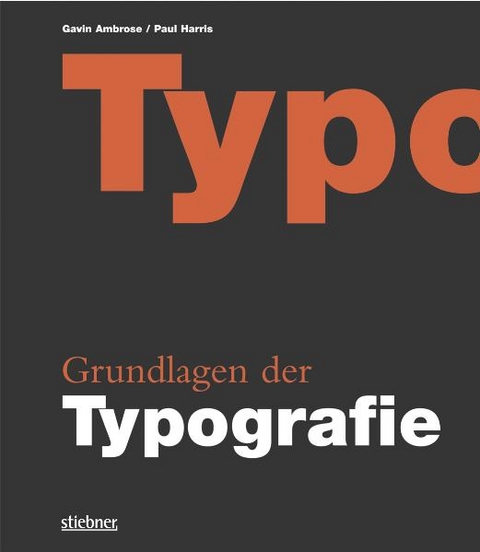
Grundlagen der Typografie
'Gute Typographie ist so, wie ein guter Diener gewesen sein mag: da und doch nicht bemerkbar; unauffällig, aber eine Voraussetzung des Wohlbefindens …', so formulierte es einmal Jan Tschichold. Um dieses hohe Ziel in der Gestaltung mit Schrift zu erreichen, ist typografisches Basiswissen allerdings unabdingbar. Die Grundlagen der Typografie faßte Gavin Ambrose daher in einem praxisnahen und gestrafften Band zusammen, der anhand vieler preisgekrönter Arbeiten aufzeigt, worauf es bei der Gestaltung von und mit Schrift wirklich ankommt. Gerade für Studierende und Newcomer ein idealer Einstieg, um sich mit den typografischen Basics vertraut zu machen und zugleich eine Ermutigung, selbst mit Schrift zu experimentieren. Denn nur wer weiß, nach welchen Regeln gespielt wird, kann das kreative Spiel auch gewinnen.
"Gavin Ambrose arbeitet als Grafikdesigner, derzeit für Kunden aus dem Kunstsektor, für Verlage und Werbeagenturen. Als Koautor und -designer veröffentlichte er mehrere Bücher zu den Themen Marken-,Verpackungs- und Editorial Design. Paul Harris ist freiberuflicher Autor, Journalist und Redakteur. Er schreibt für internationale Magazine und Journale in London und New York und war – unter anderem als Koautor – an Publikationen über Verpackungsdesign und Designprinzipien beteiligt. "